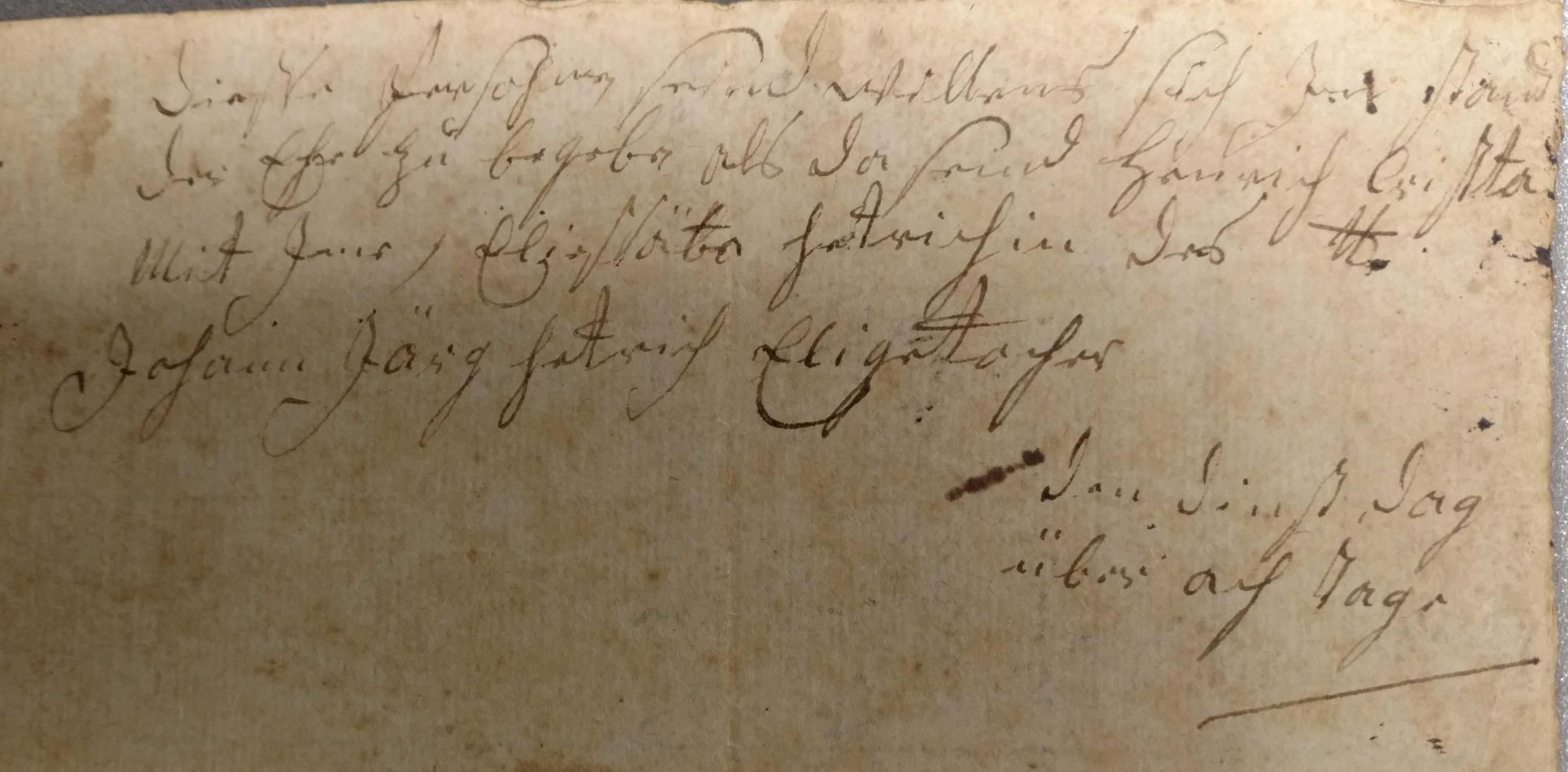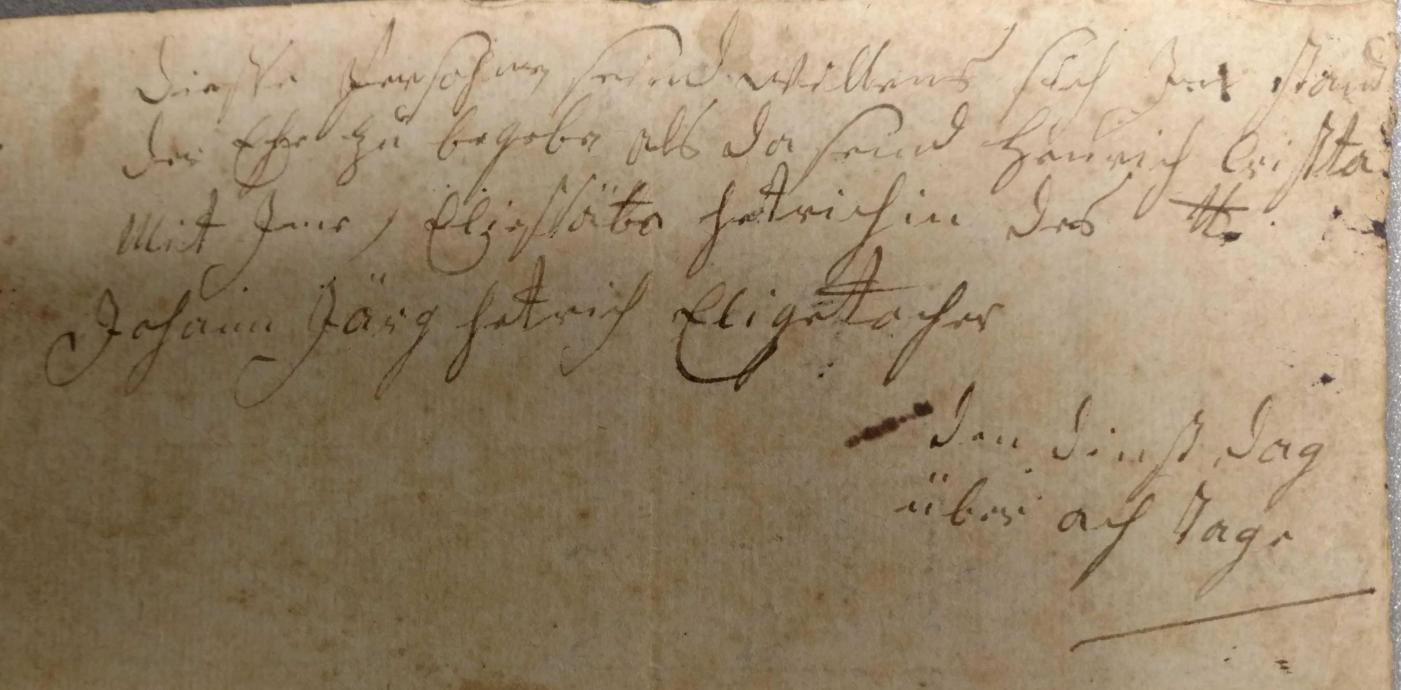
Das ist aber arg verblichen, auf den ersten Blick fällt mir  "... sind willens sich zum Stand der Ehe zu begeben als da sind Henrich Christer [.] Mit [...] Eliesbäta Hetrich ..." ins Auge. Und dann sind da noch die Rechtschreibeigenheiten ...
Dieße Persohnen seind willens sich inn stand der Ehe zu begeben als da seind Henrich Crista mit ime Eliesbäten Hetrichin des Johann Jörg Hetrich Elige toch(t)er
Den Dinstdag über ach(t) Tage
Vielleicht 2. Hälfte 18. Jahrhundert. Henrich Crista und Elisabeth Hetrich, eheliche Tochter des Johann Jörg Hetrich, wollen in acht Tagen die Ehe schließen.